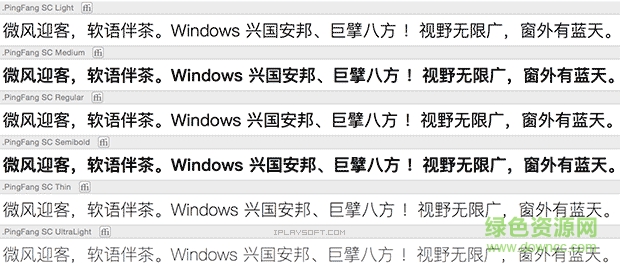
pingfang sc字体简介:
pingfang sc字体是是苹果为中国用户打造的一款富有中国元素的中文字体,这套字体包含简体以及繁体中文,共有6种字重,可以很好地满足日常设计和阅读的需求。这套字体不仅字型优美,而且也能提升在手机、电脑屏幕上的清晰度以及易读性。
字体详细介绍:
苹方字体6种字重粗细
为了让苹果的字体可以在 Windows、Android、Linux 等其他平台和设备上使用,网友已经将苹方字体全套从 Mac 系统里提取了出来,6种字重分别是极细体、纤细体、细体、常规体、中黑体、中粗体、粗体,全部都是 .ttf 格式。